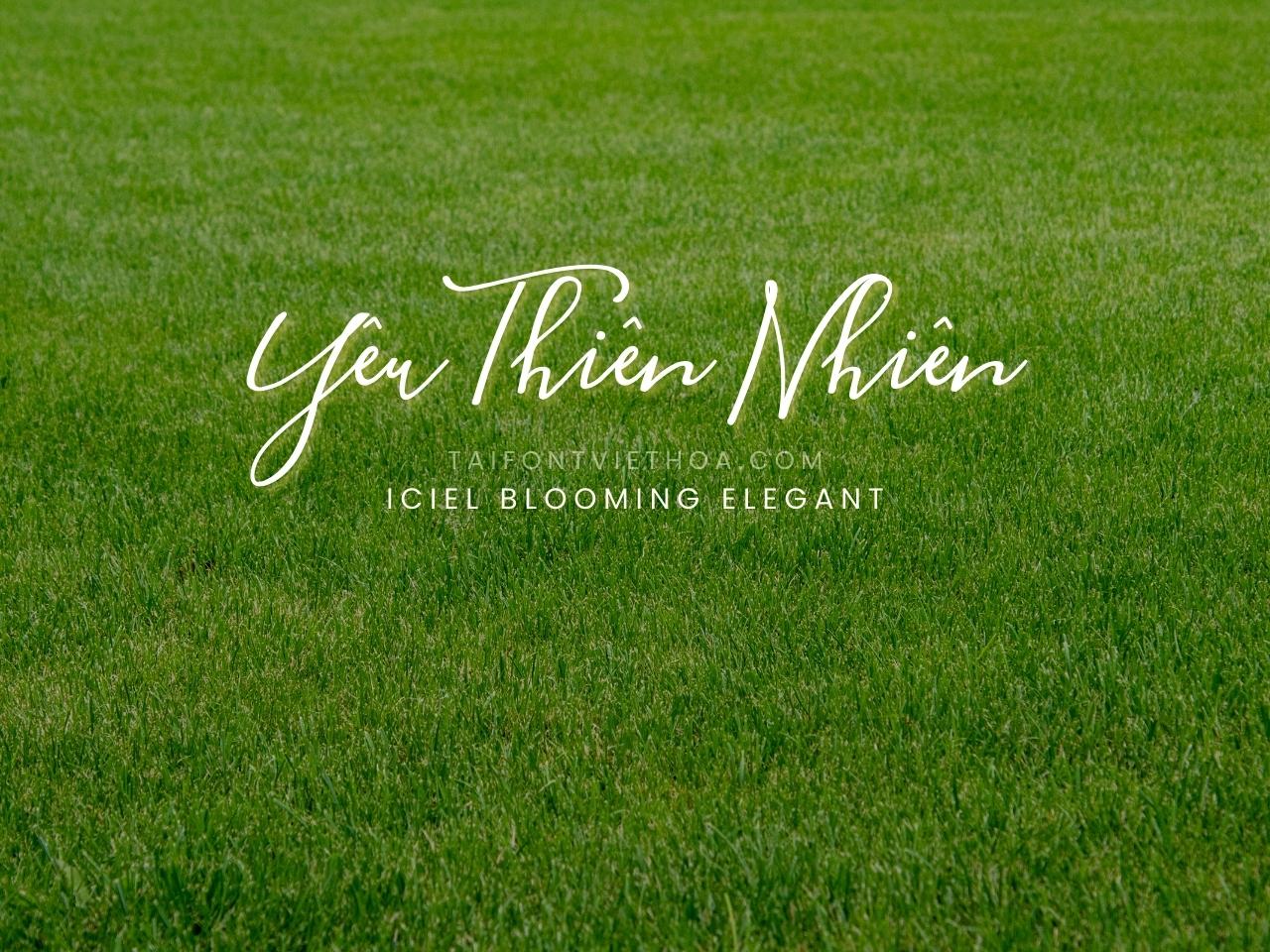
Giới thiệu về font iCiel Blooming Elegant – Bộ ba thanh lịch, lãng mạn và đậm chất nữ tính
iCiel Blooming Elegant là phiên bản Việt hóa của bộ ba font cùng tên do nhà thiết kế nổi tiếng Nicky Laatz sáng tạo. Bộ font bao gồm Regular, Script và Sans, với định hướng phục vụ các thiết kế mang tính thanh lịch, nghệ thuật và đậm chất cá nhân hóa. Phiên bản Việt hóa được iCiel thực hiện đầy đủ, hỗ trợ trọn bộ tiếng Việt và hơn 60 ngôn ngữ khác, giúp font dễ dàng ứng dụng trong các dự án quốc tế hoặc đa quốc gia.
Đặc điểm thiết kế và ứng dụng nổi bật của font iCiel Blooming Elegant
Bộ ba font trong Blooming Elegant kết hợp giữa nét viết tay mềm mại và cấu trúc sans serif thanh mảnh. Phần script bay bổng với các ligature mượt mà, giúp tạo điểm nhấn nghệ thuật cho tiêu đề hoặc chữ ký. Trong khi đó, sans và regular lại giữ được độ rõ ràng, cân đối, lý tưởng cho các đoạn mô tả hoặc thiết kế in ấn. Font mang đến cảm giác nữ tính, nhẹ nhàng nhưng vẫn chuyên nghiệp và hiện đại.
iCiel Blooming Elegant rất phù hợp với các ngành nghề như thiệp cưới, mỹ phẩm, thời trang, spa, ẩm thực cao cấp, giáo dục nghệ thuật và các thương hiệu hướng đến phụ nữ. Một số ứng dụng tiêu biểu gồm: thiết kế logo thương hiệu cá nhân, bao bì sản phẩm handmade, typography lời chúc lễ hội, thiệp cưới, poster lễ Valentine, hoặc bộ nhận diện visual thương hiệu.